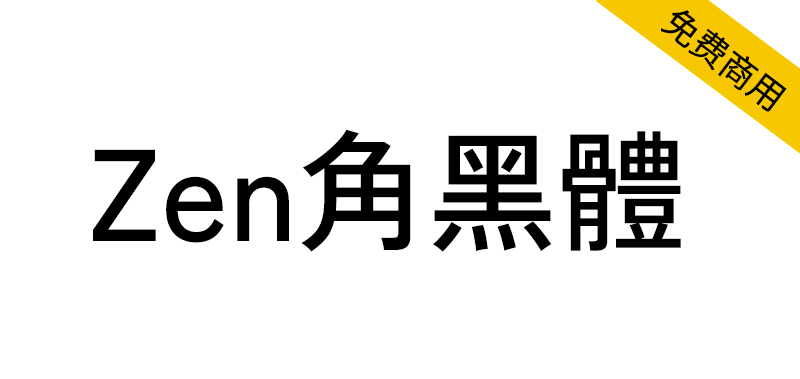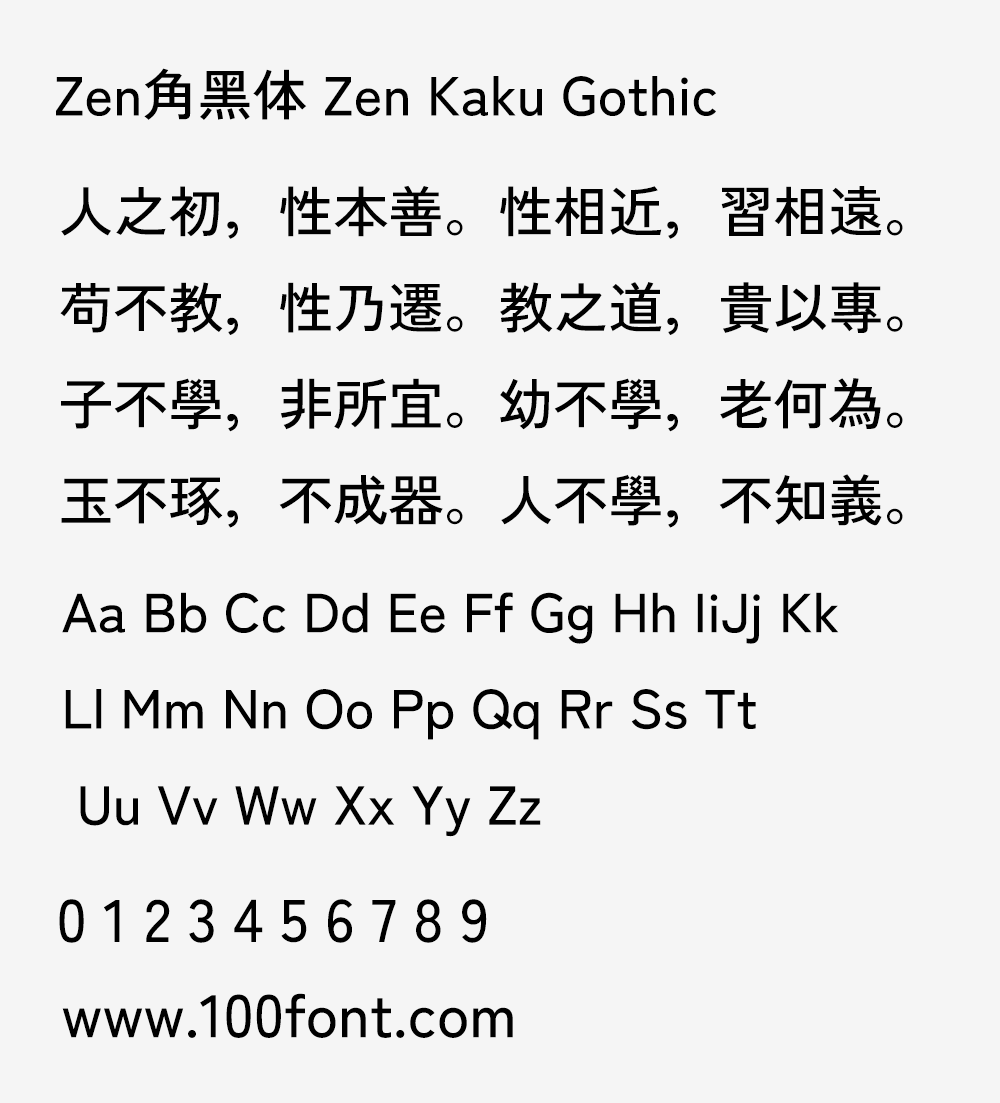
Zen角黑体(Zen Kaku Gothic)是一个基本的日本san serif(哥特式)家族。使用此字体,您可以表达精细排版,而无需任何专业的详细安排。由于独特而简单的设计,它自然具有很高的易读性。易于使用和阅读。
Zen Kaku Gothic A是一个古典而简单时尚的无衬线家庭。由于正统的字体设计,非常清晰易读。非常适合各种用法,从标题到文本,甚至标题。
Zen Kaku Gothic N is a basic Japanese san serif (Gothic) family. With this font, you can express fine typesetting without any professional detailed arrangements. Because of the unique yet simple design, it gives naturally high legibility. Easy to use and read.
Zen Kaku Gothic A is a classical yet simple and stylish sans serif family. Highly legible due to orthodox letterform design. Great for various usage, from title to text, and even caption.